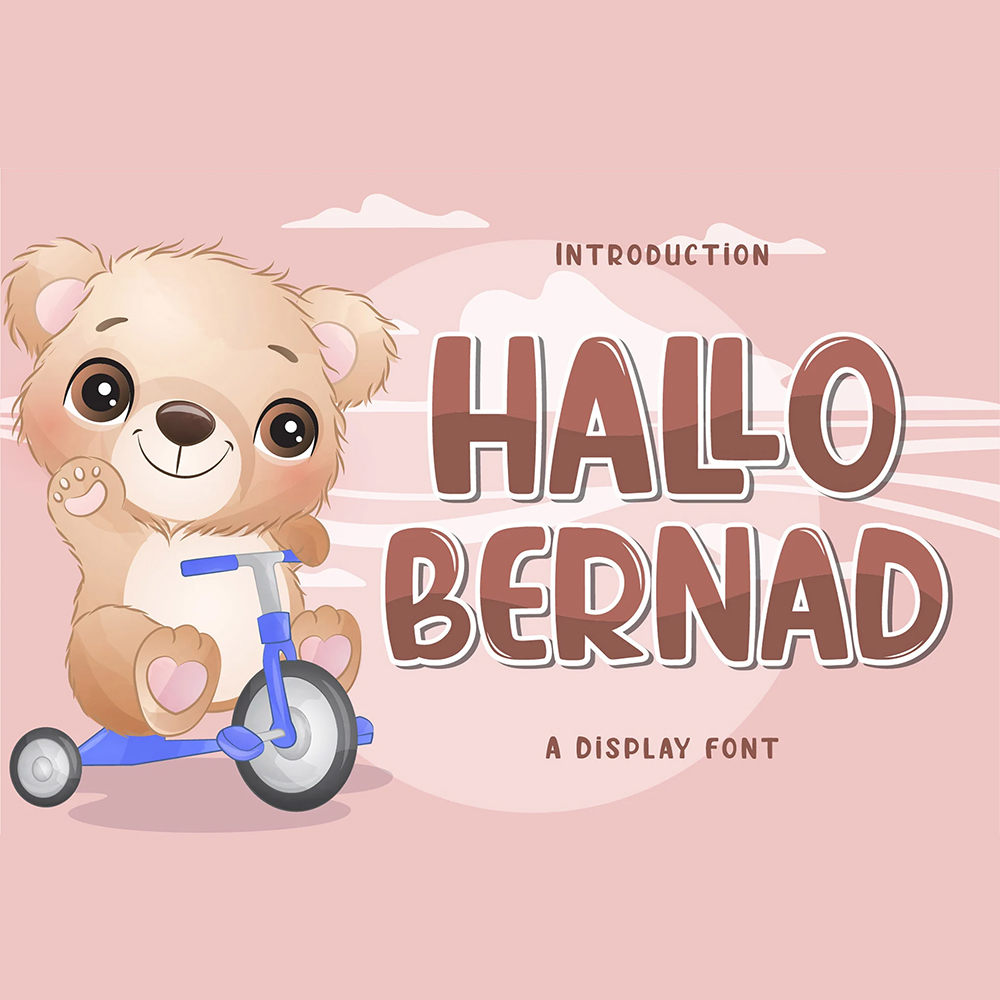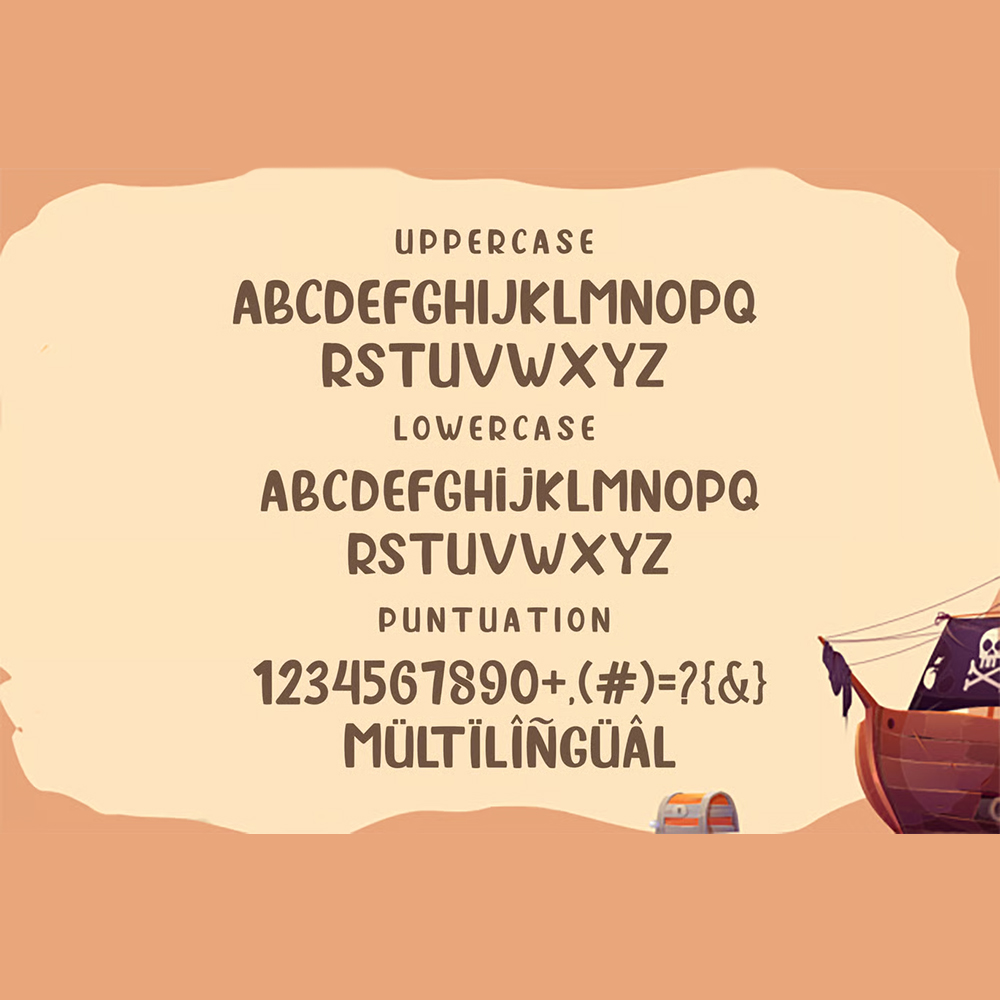
فونت پرمیوم و انگلیسی Hallo Bernad Font یک فونت نمایشی زیبا برای انواع طرحها است. هالو برناد را میتوان برای محصولاتی مانند صنایع دستی، بستهبندی محصول، نقل قولها، طراحی محصول، هنرمندان، برچسبها، عکاسی، واترمارک، لوگو و برندسازی استفاده کرد.
مزایای استفاده از فونت لاتین Hallo Bernad Font چیست؟